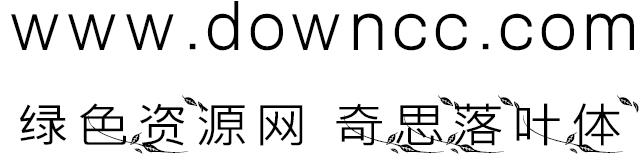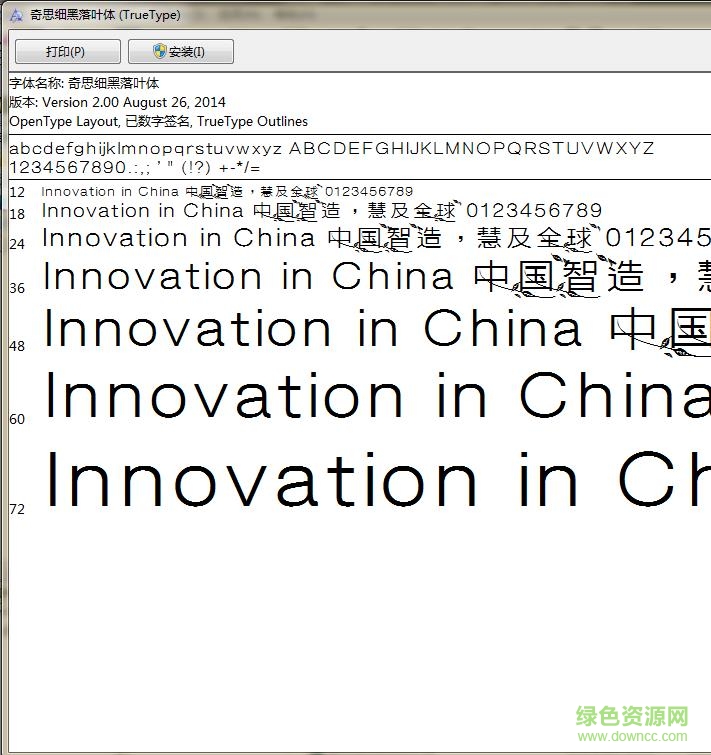
奇思落葉體ttf百度云以其每一個(gè)都帶來落葉而得名,是一款十分不錯(cuò)的字體文件,這款字體的運(yùn)用效果十分不錯(cuò),受到了萬千用戶們的喜愛!
奇思落葉體ttf官方介紹
這款字體在每一個(gè)自行結(jié)構(gòu)上增加了落葉效果,從而能夠達(dá)到讓人驚艷的視覺體驗(yàn),在眾多行業(yè)中廣泛運(yùn)用!
奇思細(xì)黑落葉體字體介紹